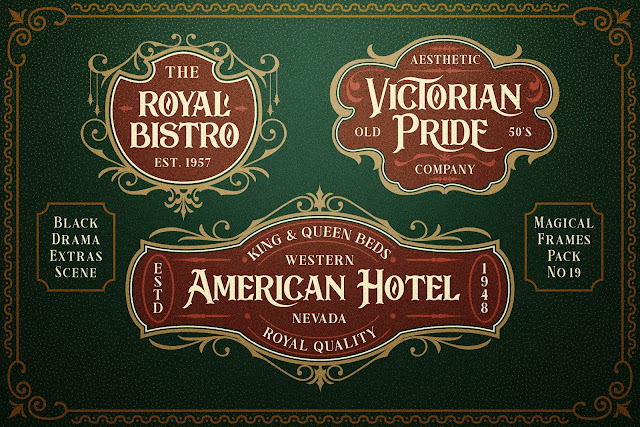
La tipografía que hoy os traemos en descarga directa gratuita se podría definir de forma rápida en ornamental y elegante. Esta tipografía es Black Drama de Iancetype desde Indonesia.
Al descargar Black Drama obtienes un gran trabajo por parte de su diseñador ya que esta tipografía viene muy cargada de florituras, ligaduras y caracteres alternativos que harán de nuestros diseños algo diferente y llamativo.